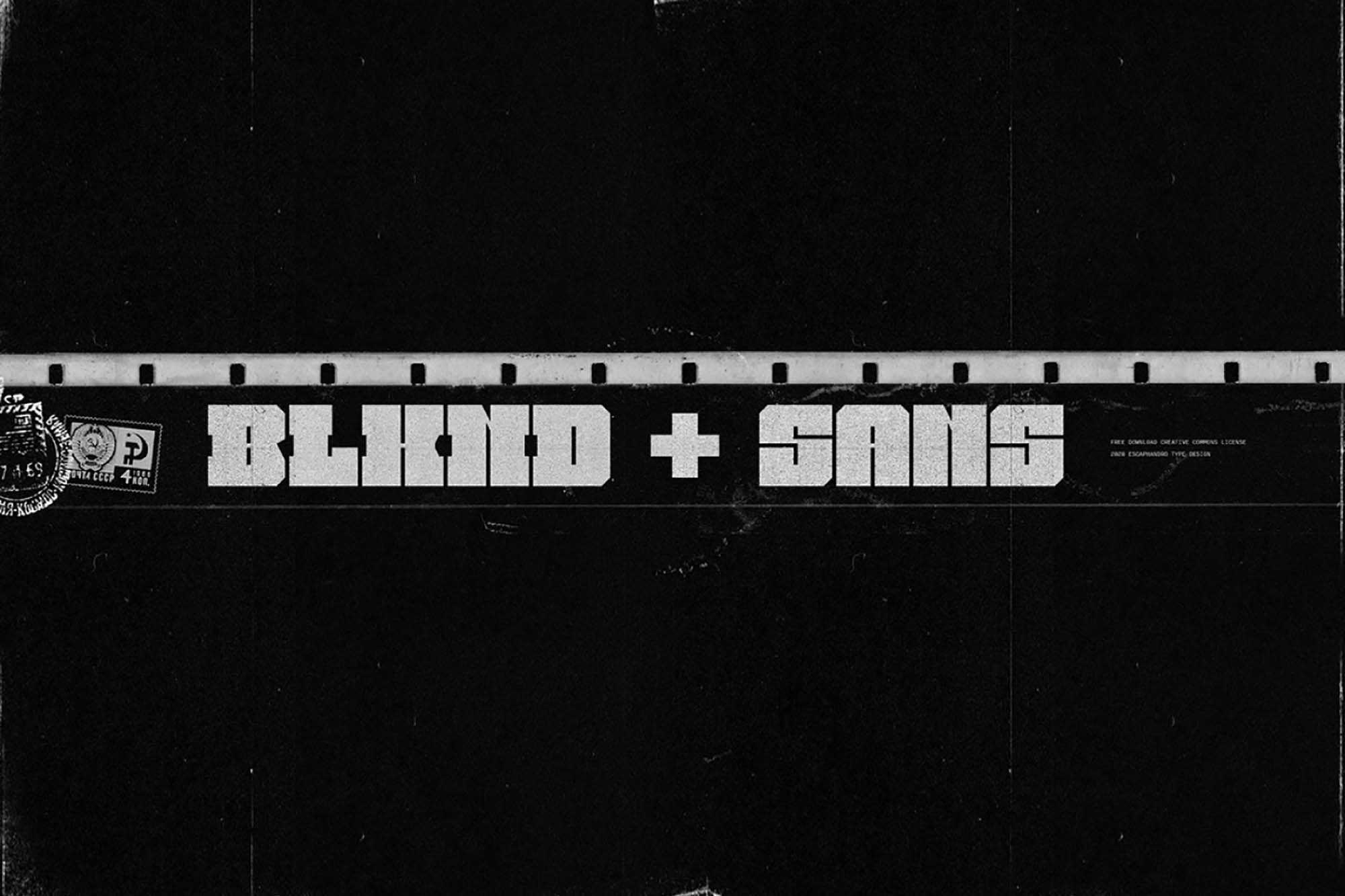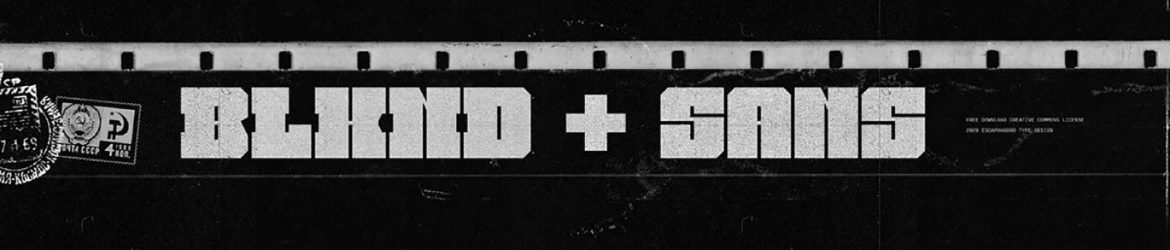
BLKND Free Display Font – Download Grátis
Descubra a verdade por trás do nome ‘BLKND’. Este novo tipo de fonte é um desafio de linguagem: sem vogais, seus usuários são obrigados a pensar rapidamente sobre os primeiros termos que podem surgir na mente quando veem os caracteres. É um ‘blackened’ ou um ‘blinked’? Ou talvez ambos? Este novo recurso não revela o significado verdadeiro da palavra, mas uma vez instalado, ele oferece uma oportunidade única de explorar sua originalidade única. Seja para criar headlines ou títulos arrasadores, ‘BLKND Free Display Font’ traz uma nova perspectiva para sua identidade visual, sem deixar de lado a sua originalidade. Baixe-o agora e descubra a diferença que uma fonte de tipo diferente pode fazer em seu trabalho.